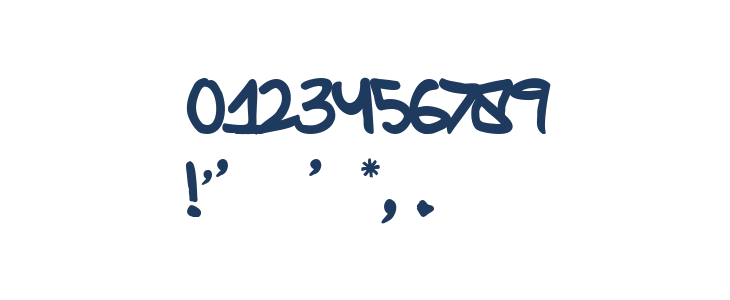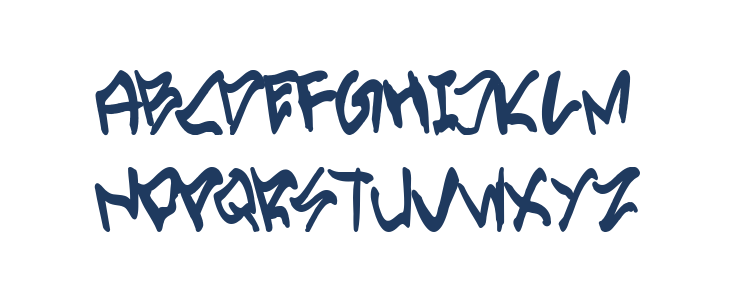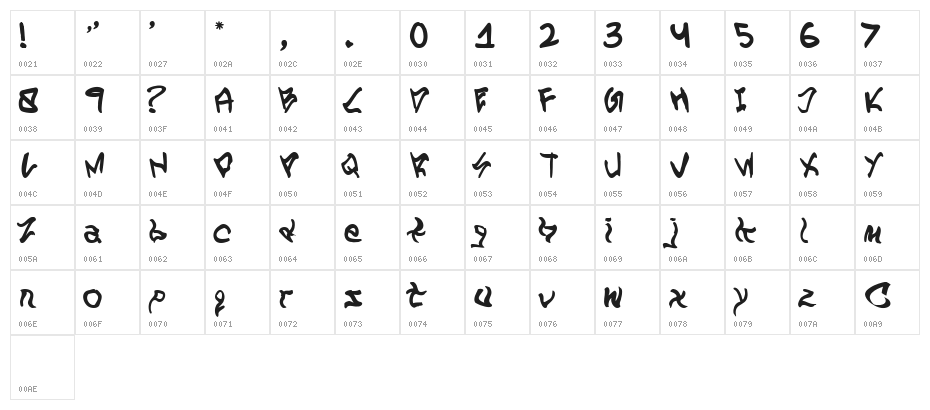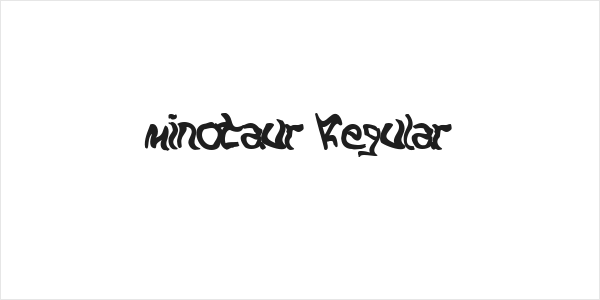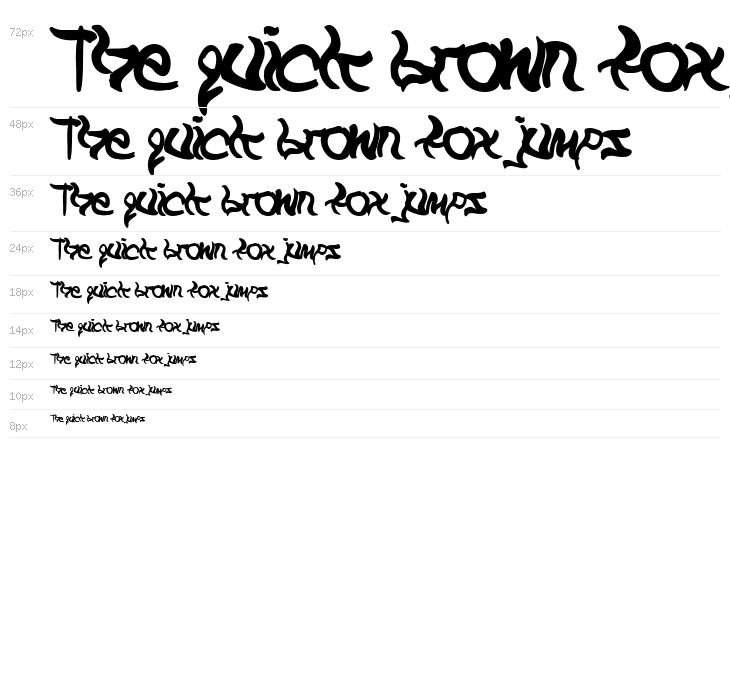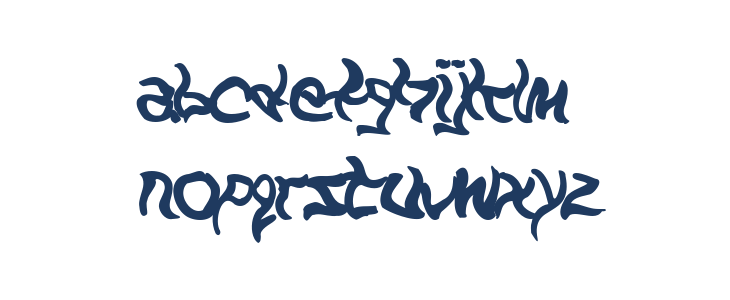
minotaur Regular Font
| Stile generale | Decorative, Urban, Expressive |
| Caso d'uso | Logos, Headlines, Posters, Artistic projects |
| Progetti proposti | Street art posters, music album covers, urban branding, event flyers, creative headlines. |